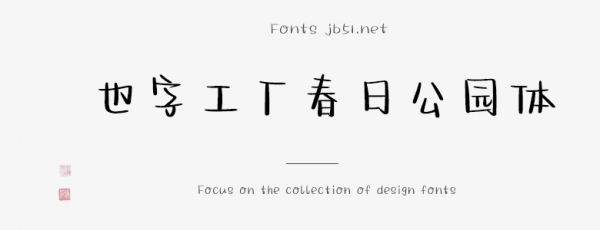
也字工廠春日公園體是由也字工廠出品的藝術(shù)字體,字體筆觸適中,字形端正,具有很好的視覺感,適合應(yīng)用于藝術(shù)設(shè)計(jì)、平面宣傳設(shè)計(jì)、網(wǎng)頁(yè)設(shè)計(jì),書法字帖等領(lǐng)域,需要的朋友可以前來(lái)本站下載。